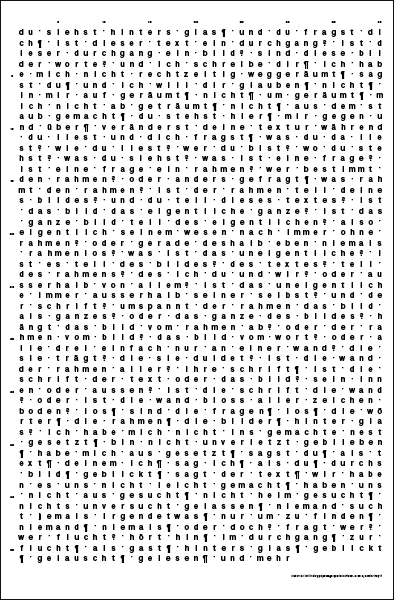
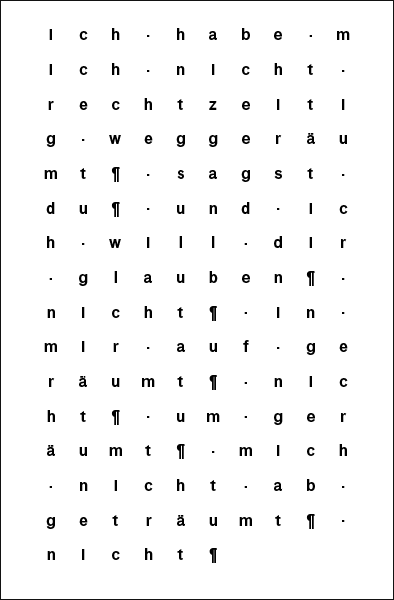
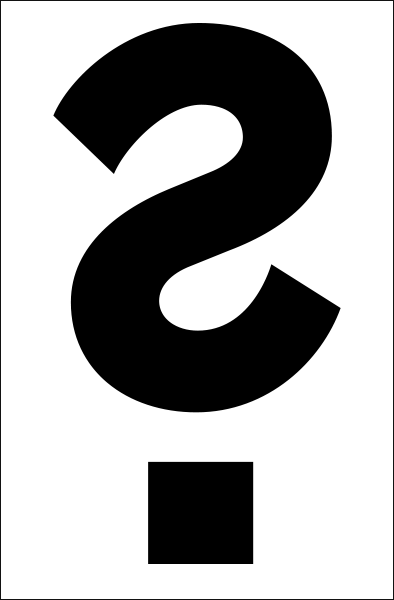
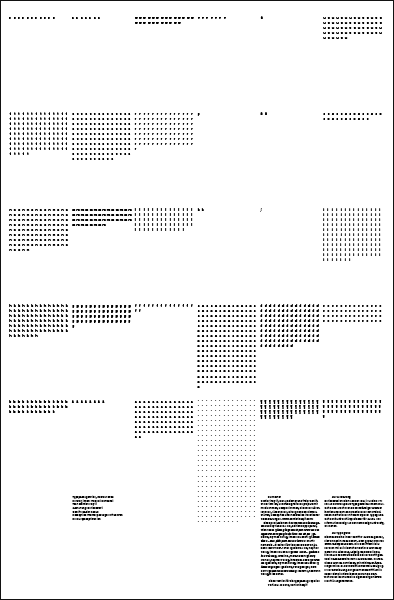
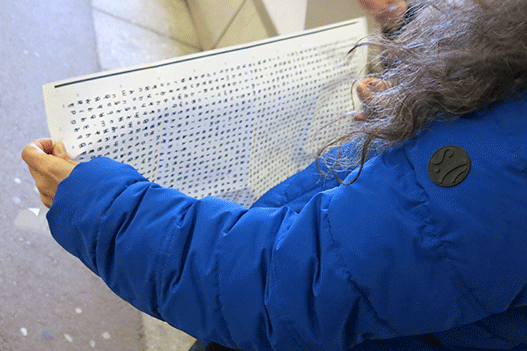
Typografie
Die Plakate sind in der Schrift F Grotesk gesetzt, die von Radim Peško 2007–2011 gestaltet wurde. Die Schriftfamilie ist nur zum Teil auf die Breite Halbfette Grotesk by Schelter & Giesecke, Leipzig (1890) zurückzuführen. Ab 1900 wurde diese bei der Schriftgiesserei Haas als Breite Fette Grotesk bzw. Französische Grotesk vertrieben, mit minimalen Änderungen wie z. B. das vereinfachte zweistöckige g. In der Entwicklung der gesamten Schriftfamilie haben sich die historischen Merkmale stark weiterentwickelt und eine eigene zeitgemäßere Identität angenommen. www.radimpesko.com